Font script adalah jenis font yang hampir mirip dengan font handwriting karena desainnya yang meniru gaya tulisan tangan manusia. Namun, font script memiliki sentuhan artistik yang lebih kuat, desain yang lebih rumit, dan karakteristik yang lebih menonjol.
Biasanya, font script digunakan untuk memberikan nuansa elegan, artistik, dan profesional pada berbagai jenis desain. Hal ini membuatnya sangat cocok untuk proyek-proyek desain yang membutuhkan kesan eksklusif, seperti kartu undangan, kartu ucapan, logo, hingga poster dan lainnya. Nah, dalam artikel ini, kami telah mengumpulkan 40 koleksi font script keren dan unik yang siap untuk Anda unduh dan pakai secara gratis! Langsung saja simak daftarnya di bawah ini!
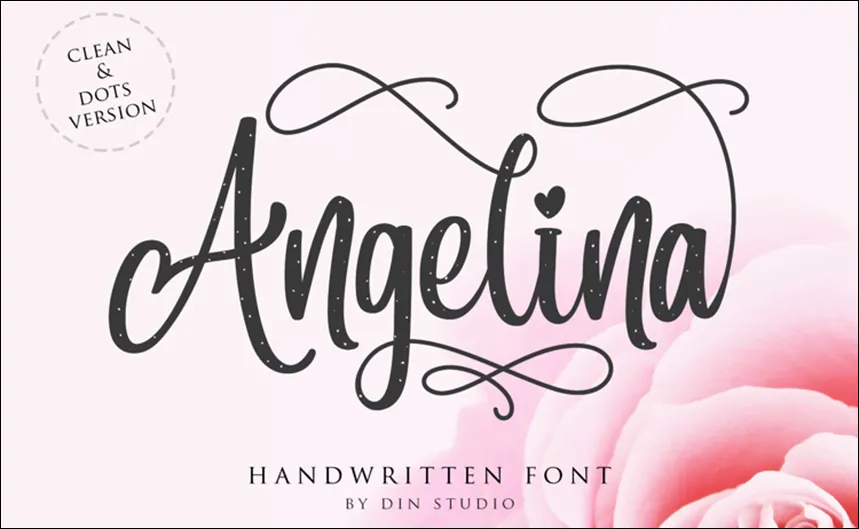
Font pertama adalah Angelina. Font ini memiliki desain yang elegan dengan garis-garis yang halus, cocok untuk proyek-proyek yang membutuhkan sentuhan feminin dan mewah, seperti undangan pernikahan, logo, dan lain sebagainya.
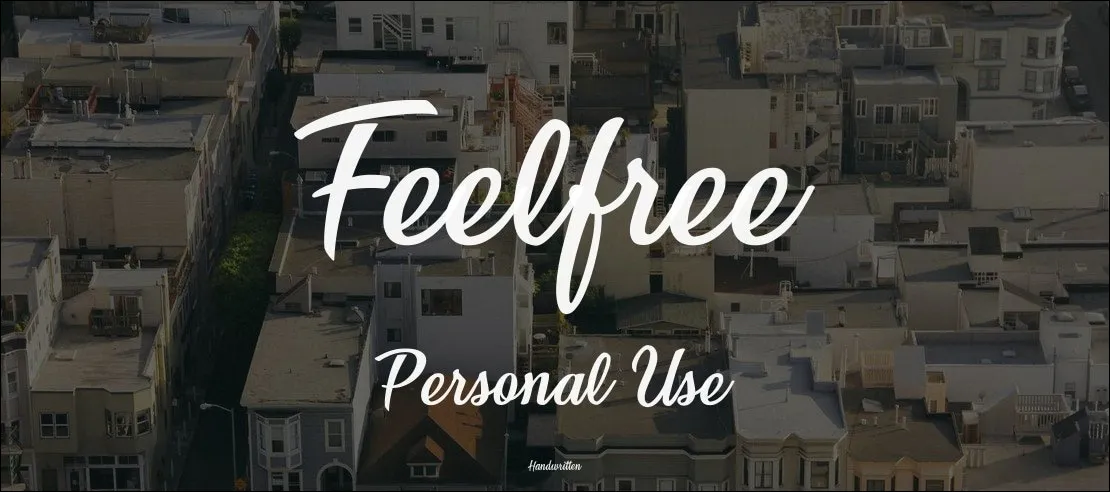
Font kedua adalah Feelfree. Font ini memiliki gaya yang lebih santai dan bebas, dengan huruf-huruf kursif yang terlihat seperti ditulis tangan, cocok untuk proyek-proyek yang ingin terlihat lebih personal dan ramah, seperti kartu ucapan atau blog pribadi.
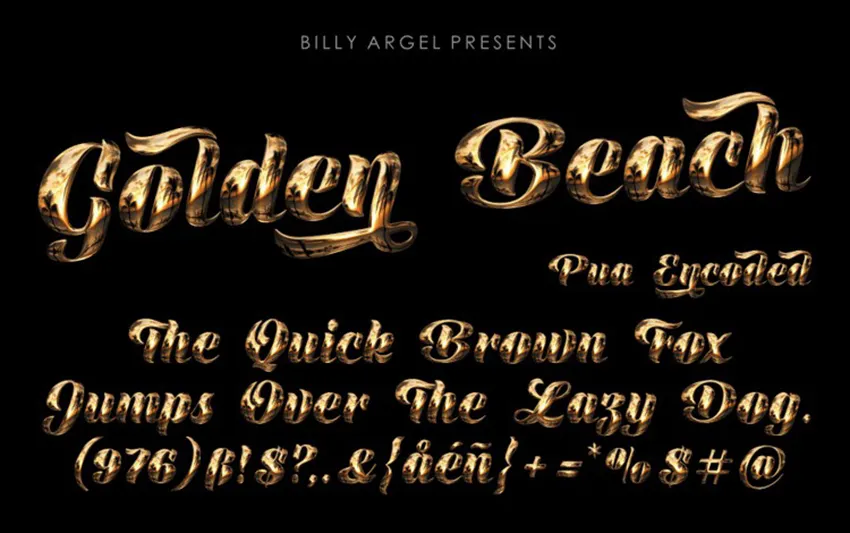
Selanjutnya adalah Golden Beach, font sans-serif yang menggabungkan unsur-unsur klasik dan modern, dengan detail yang halus dan artistik. Cocok digunakan untuk proyek desain yang membutuhkan sentuhan kesan mewah dan eksklusif, seperti logo perusahaan atau branding produk premium.
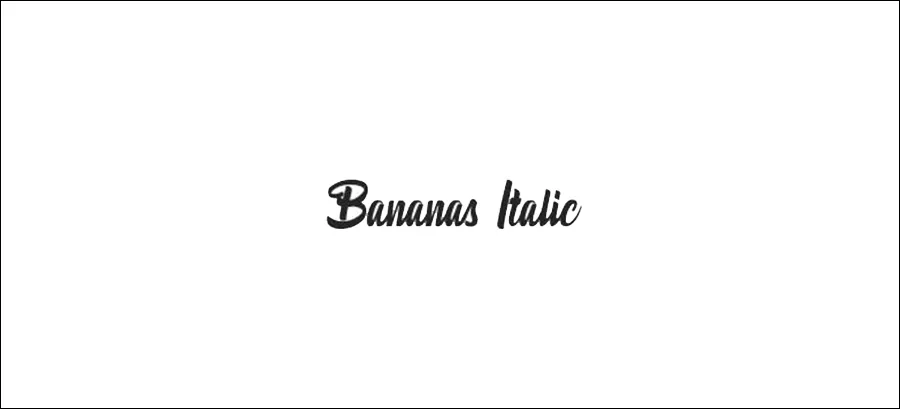
Bananas Italic menampilkan gaya tulisan yang unik dengan kemiringan miring yang mencolok. Cocok digunakan untuk desain-desain yang ingin menonjolkan kreativitas dan keunikan, seperti poster acara atau desain merchandise.
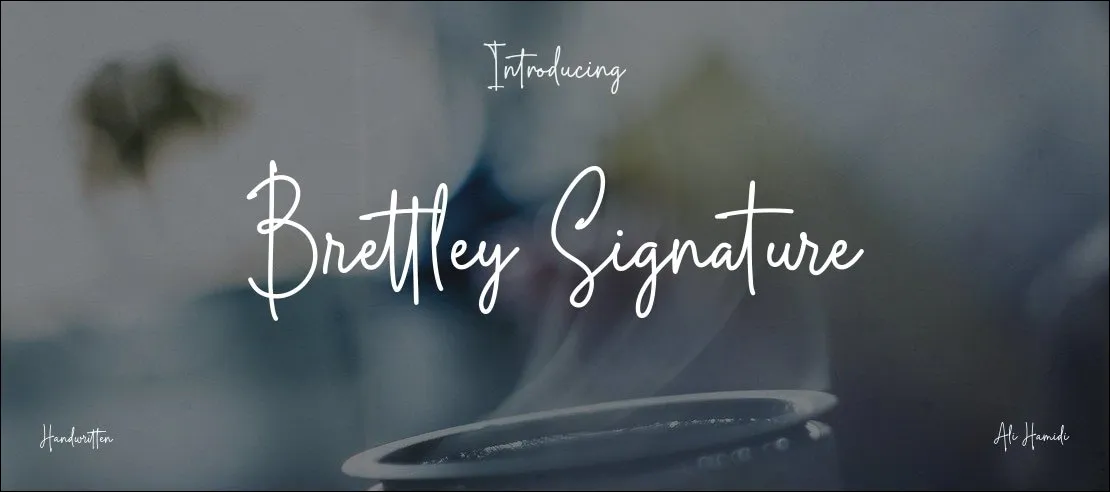
Brettley Signature adalah font kursif yang memberikan kesan elegan dan eksklusif dengan detail yang halus dan anggun. Cocok digunakan untuk proyek desain apapun.
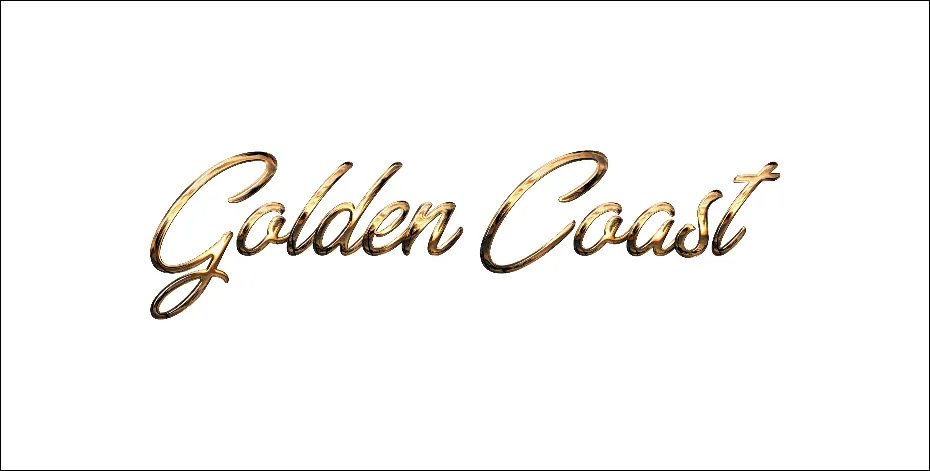
Golden Coast adalah font yang menampilkan nuansa yang ceria dan santai dengan detail yang halus dan atraktif. Cocok digunakan untuk proyek desain yang ingin menampilkan kesan keceriaan dan kehangatan, seperti desain kemasan atau branding pariwisata, dan lain-lain.
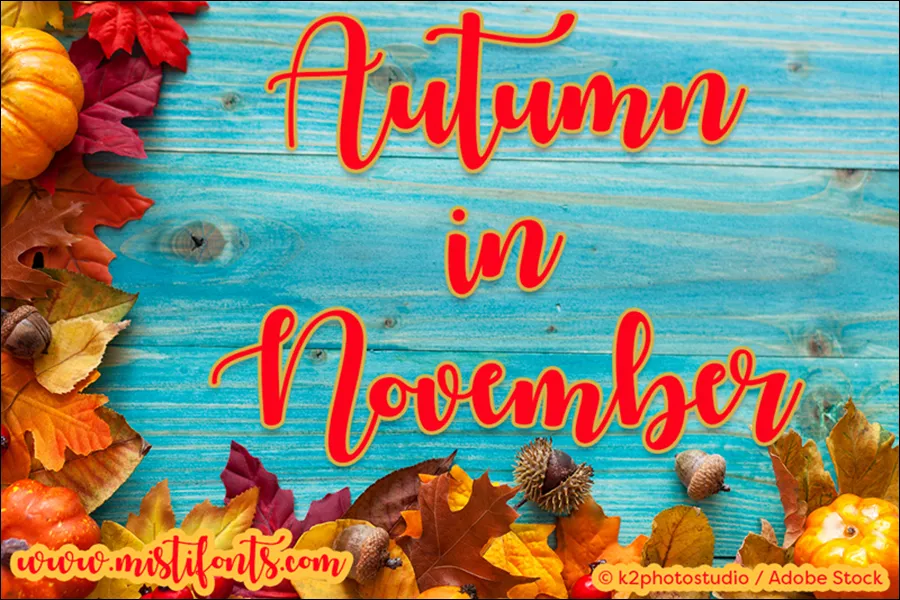
Sebagaimana namanya, font ini menampilkan huruf-huruf yang terinspirasi oleh musim gugur, dengan garis-garis yang hangat dan lembut, cocok untuk proyek-proyek yang ingin menampilkan nuansa musim gugur atau kesan yang romantis, seperti kartu ucapan atau desain interior.
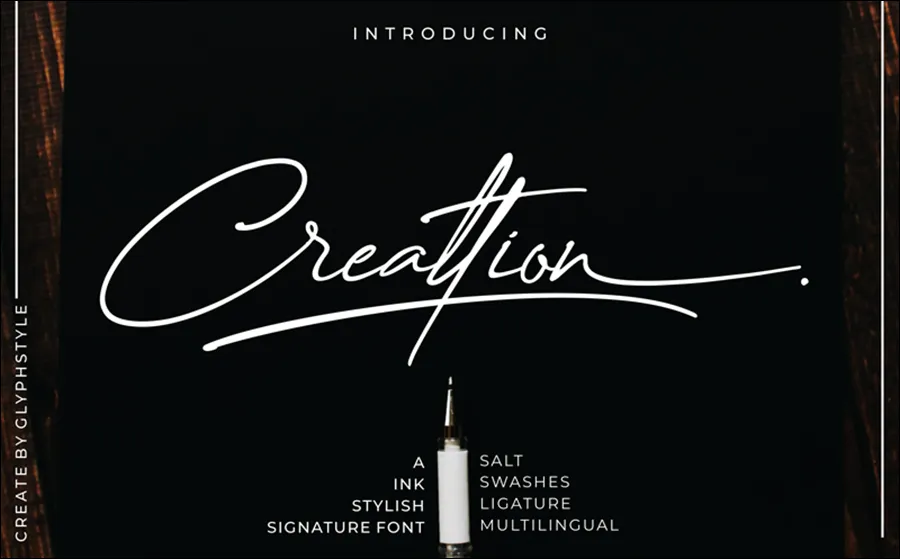
Creattion adalah font yang menampilkan gaya tulisan tangan yang kreatif dan eksentrik dengan detail yang unik dan menarik. Cocok digunakan untuk proyek desain yang ingin menonjolkan kreativitas dan keunikan, seperti desain produk atau poster seni.
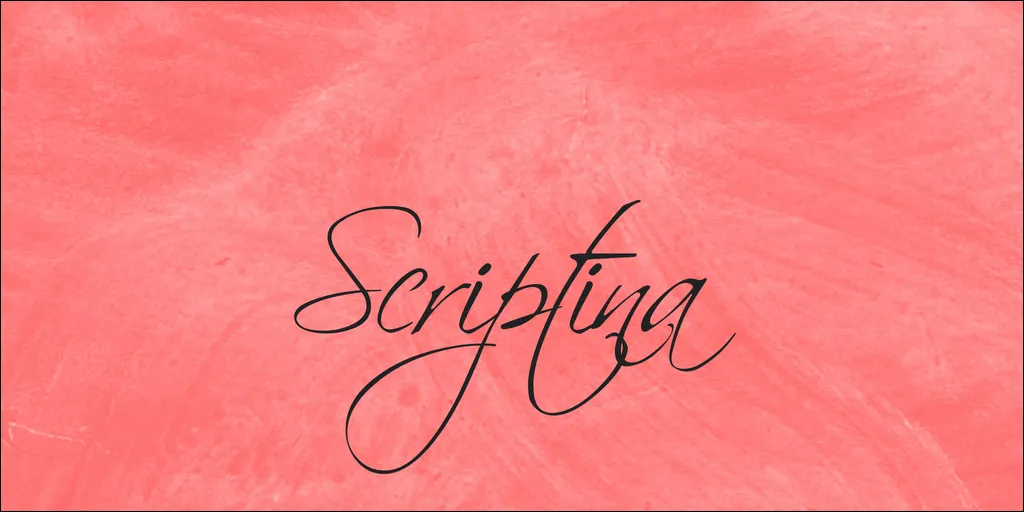
Scriptina memiliki desain yang elegan dan berliku-liku, cocok untuk proyek-proyek yang membutuhkan sentuhan feminin dan romantis, seperti undangan pernikahan, branding produk wanita, dan lain sebagainya.
Southam Demo adalah font yang menampilkan nuansa yang elegan dan profesional dengan detail yang halus dan rapi. Cocok digunakan untuk proyek desain yang membutuhkan sentuhan kesan kemewahan, seperti brosur perusahaan atau desain identitas merek.
Anydore adalah font yang memiliki gaya tulisan tangan bold dan elegan, dengan detail yang mencolok dan unik. Cocok digunakan untuk proyek desain yang ingin menampilkan keceriaan dan semangat, seperti poster acara, desain merchandise, dan lain-lain.
Billy Argel Font menampilkan gaya tulisan tangan yang kasual dan berani dengan detail yang mencolok dan eksentrik. Cocok digunakan untuk proyek desain yang ingin menonjolkan kepribadian dan keberanian, seperti desain kaos atau poster acara musik.
Blacksword adalah font yang memberikan kesan misterius dan elegan dengan garis-garis yang kuat dan tegas. Cocok digunakan untuk proyek desain yang ingin menampilkan nuansa keanggunan dan ketegasan, seperti desain logo atau materi promosi acara formal.
Little Lord Fontleroy NF memiliki nuansa klasik dan anggun dengan garis-garis yang halus dan rapi. Cocok digunakan untuk proyek desain yang membutuhkan sentuhan kesan kemewahan dan tradisional, seperti kartu ucapan atau branding produk bergaya klasik.
Hampir mirip dengan font sebelumnya, Fontleroy Brown NF memberikan kesan vintage dan retro dengan detail yang klasik dan menarik. Cocok digunakan untuk proyek desain yang ingin menampilkan nuansa nostalgia dan keunikan, seperti desain produk atau poster acara tahunan, dan lain-lain.